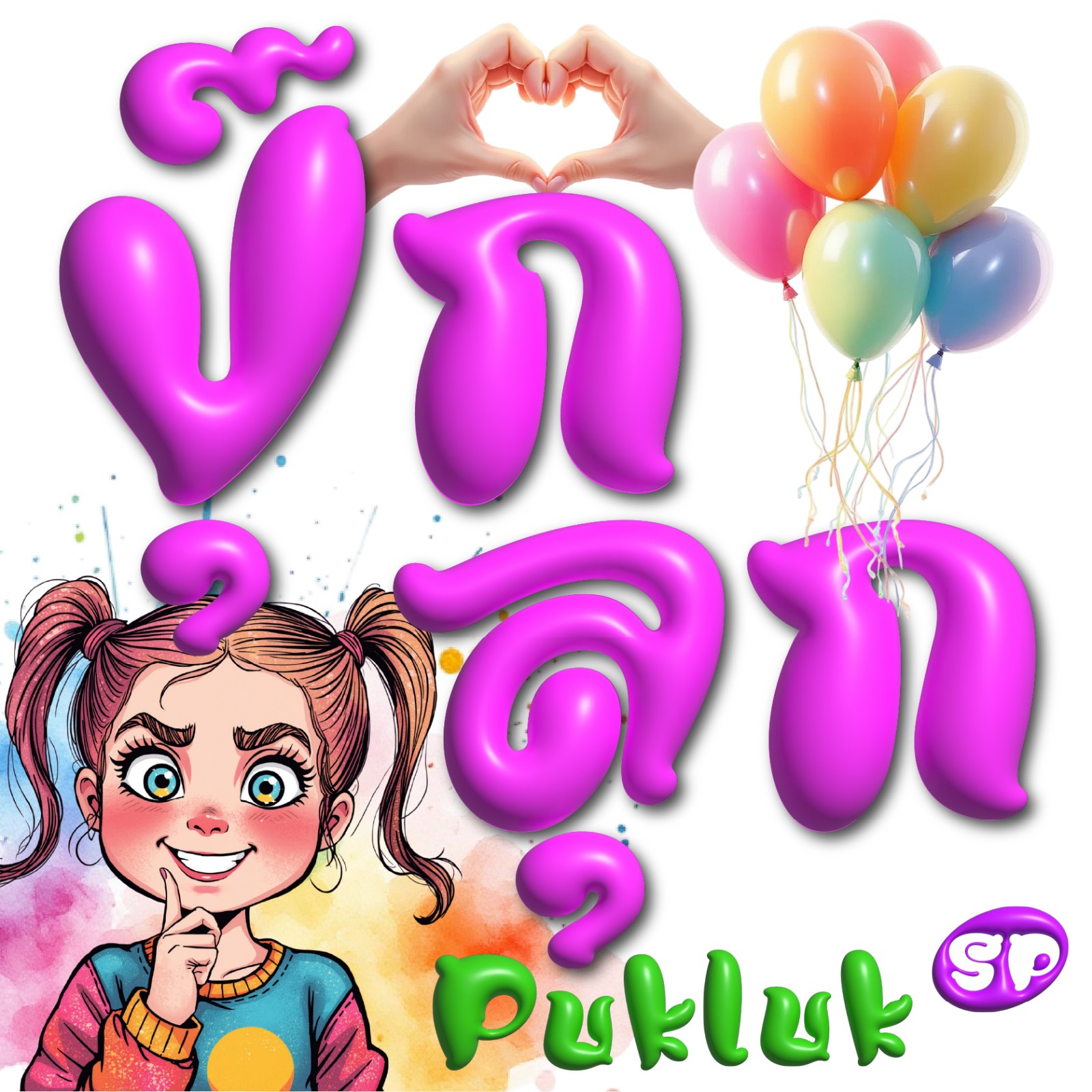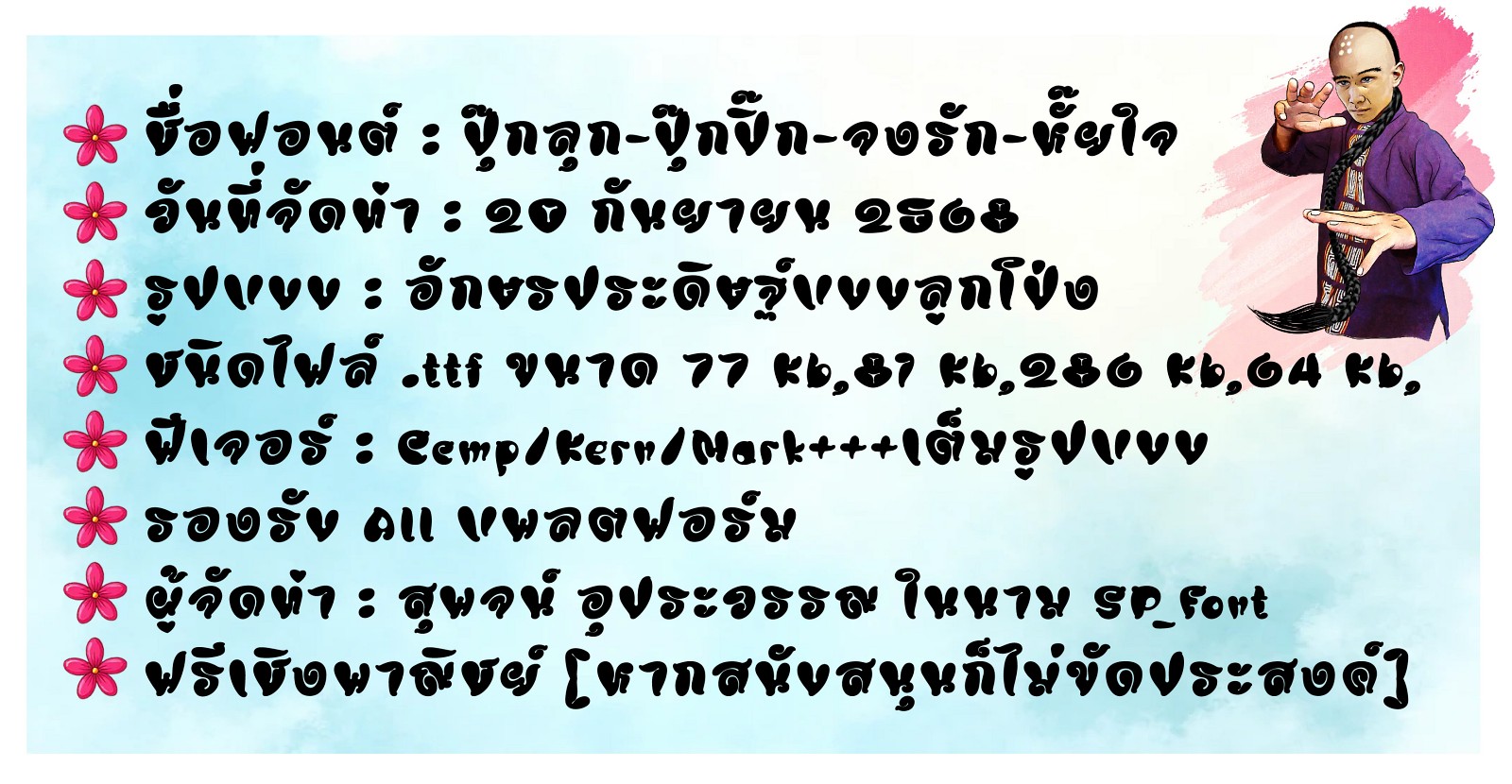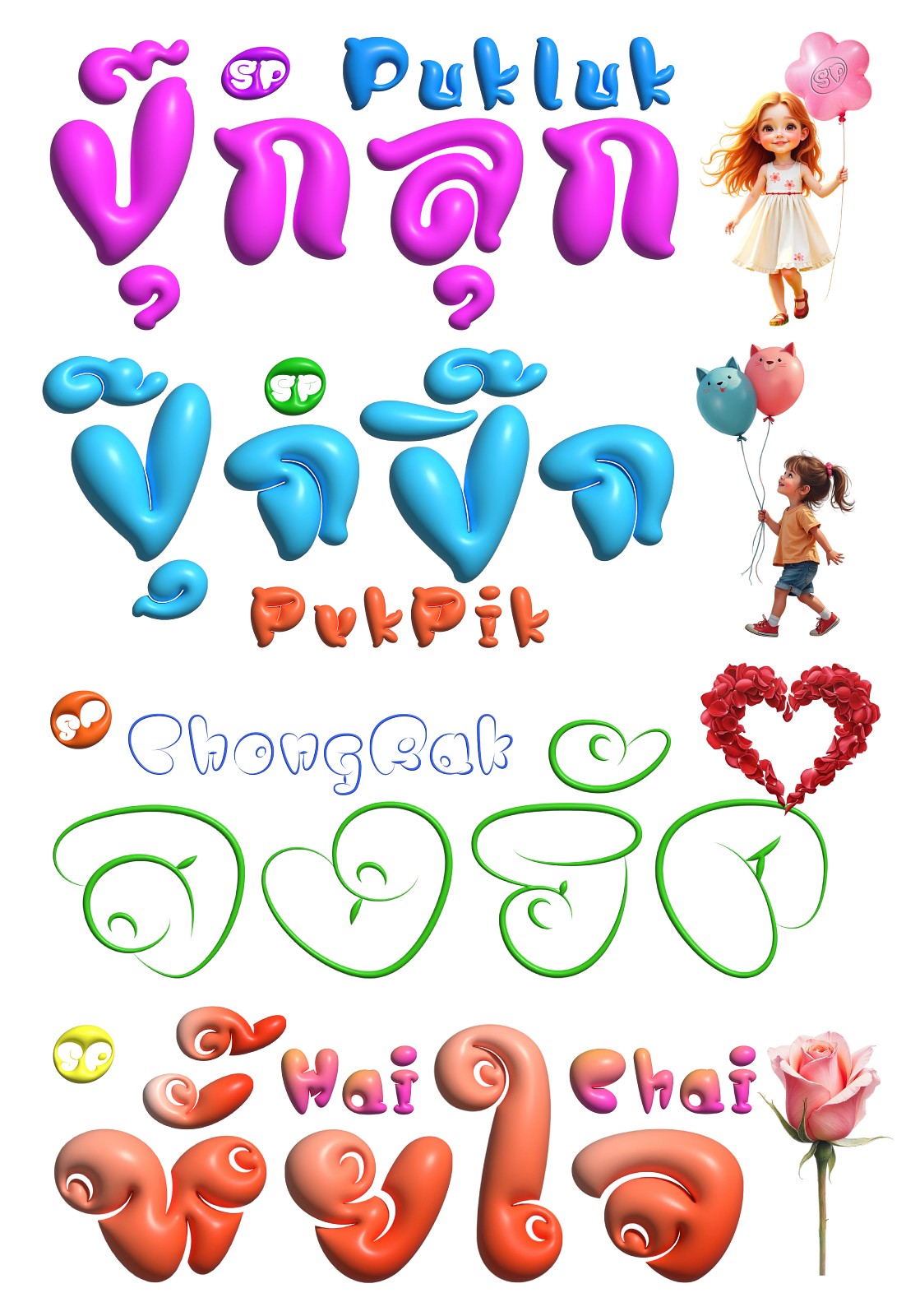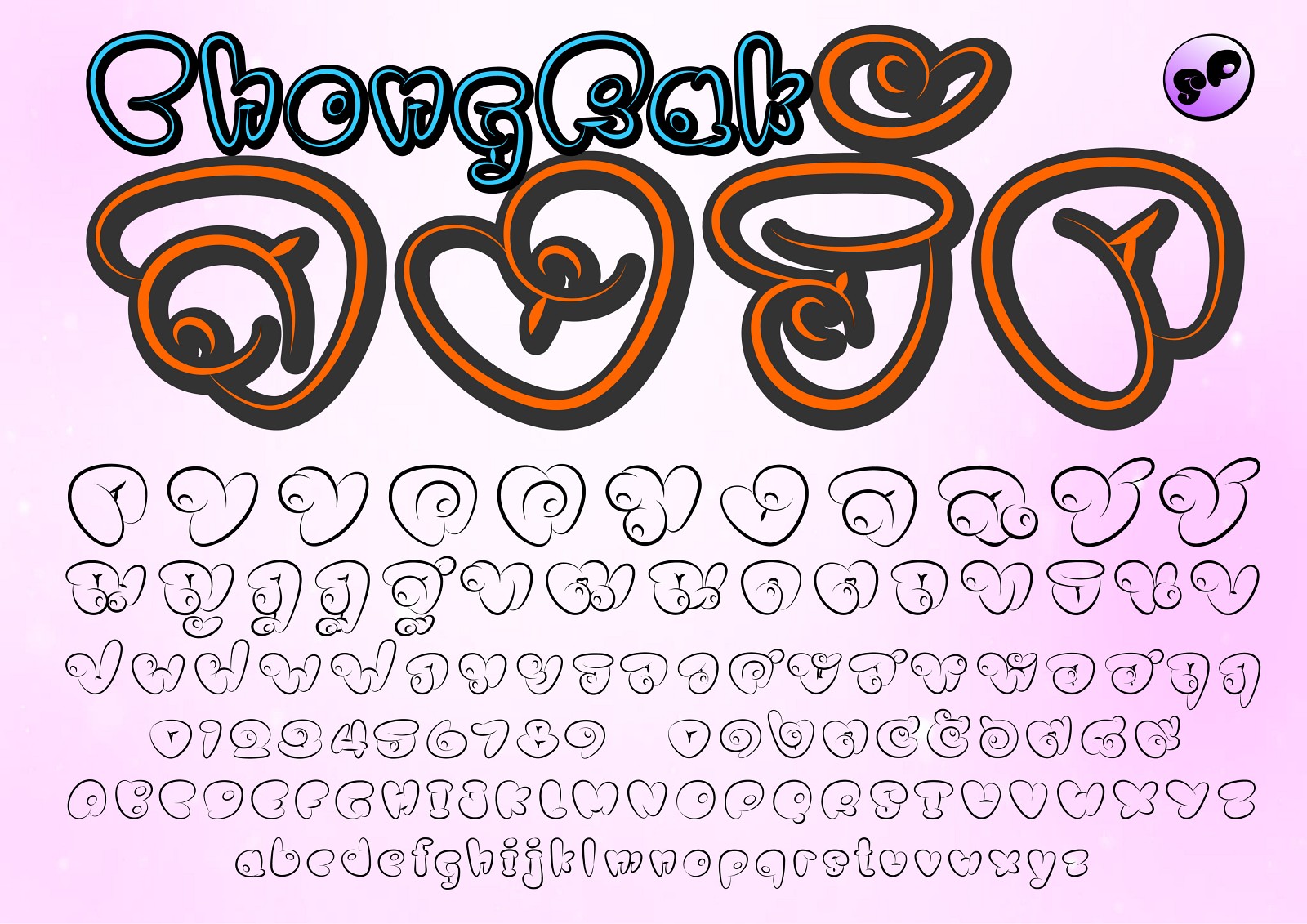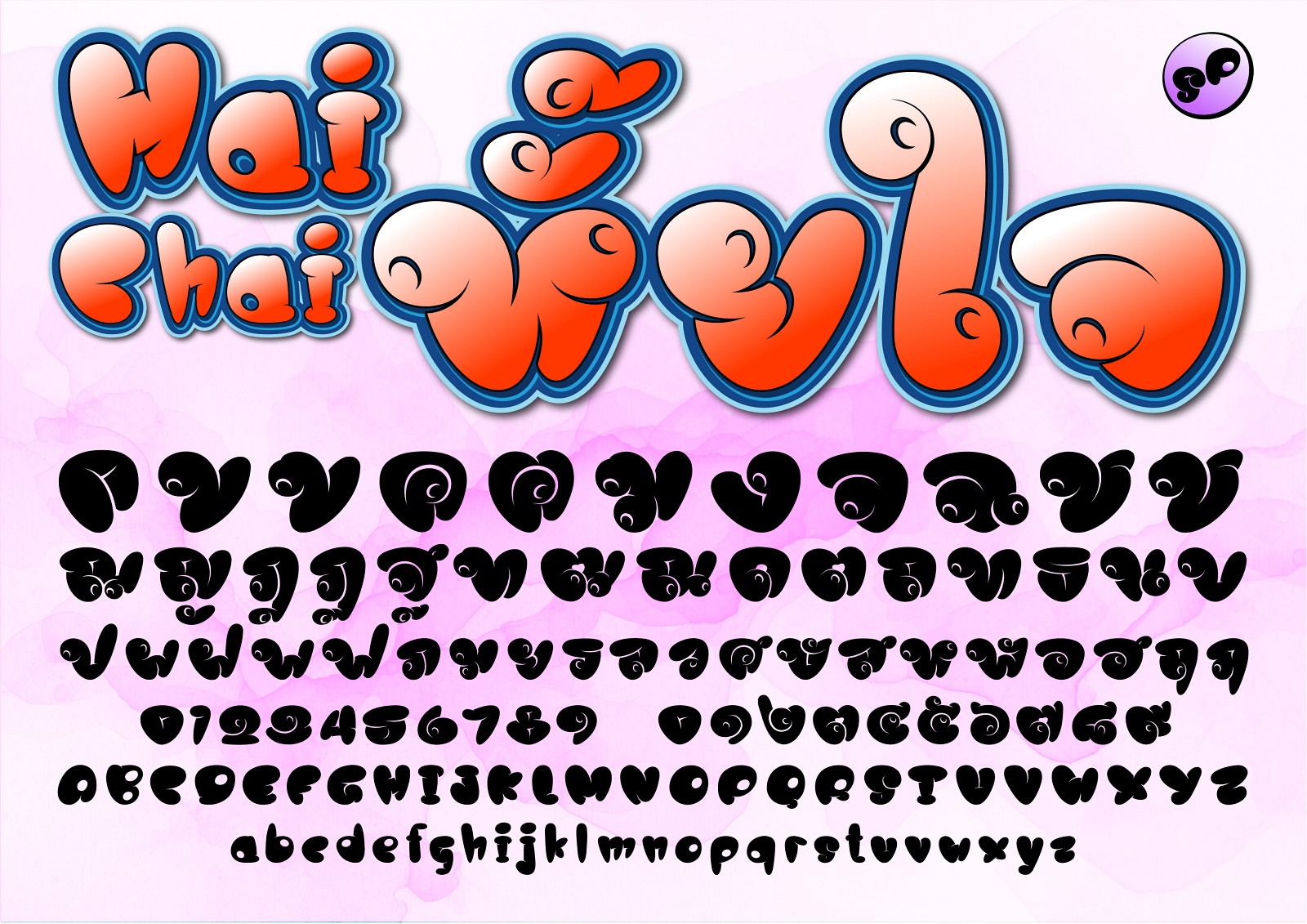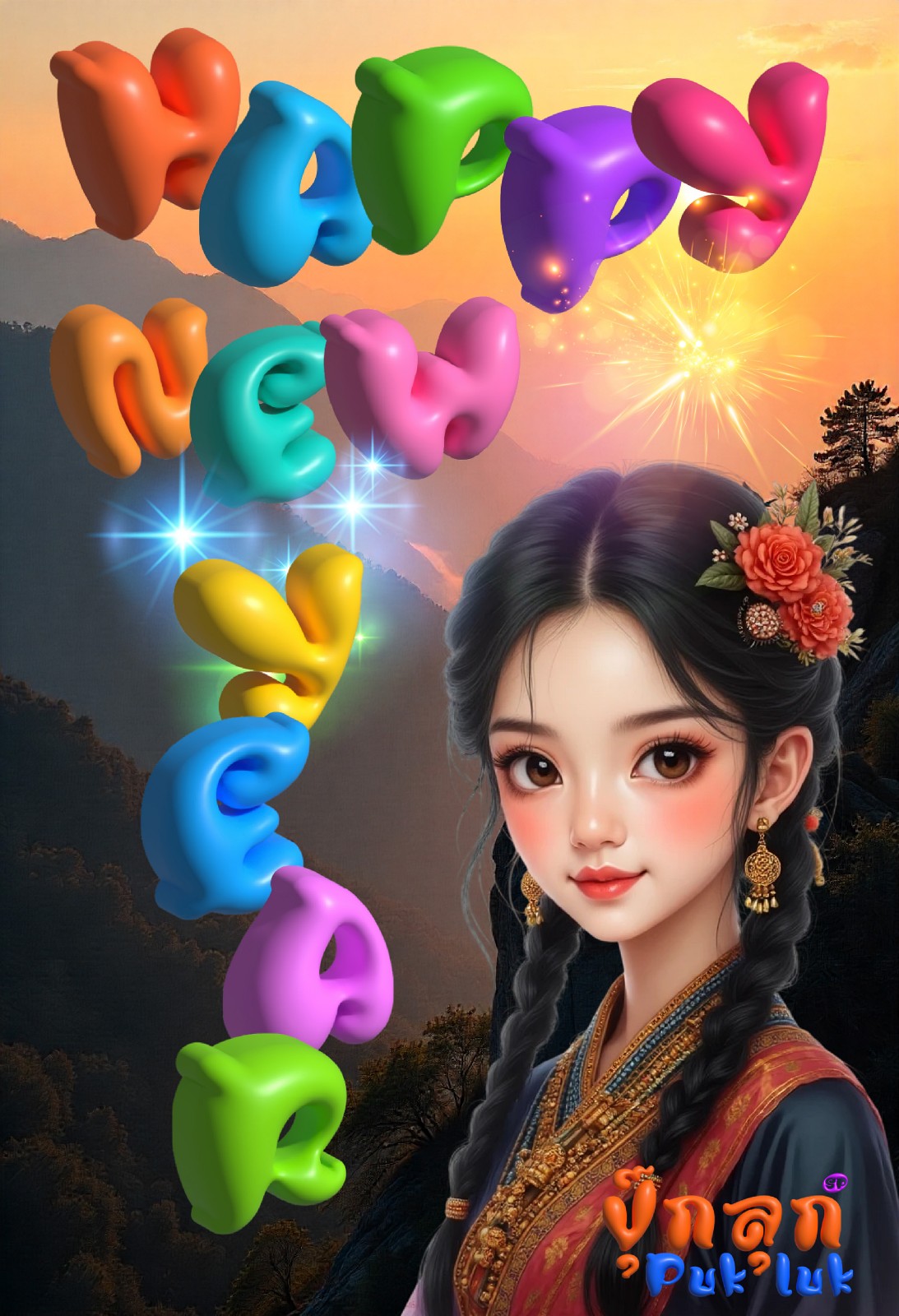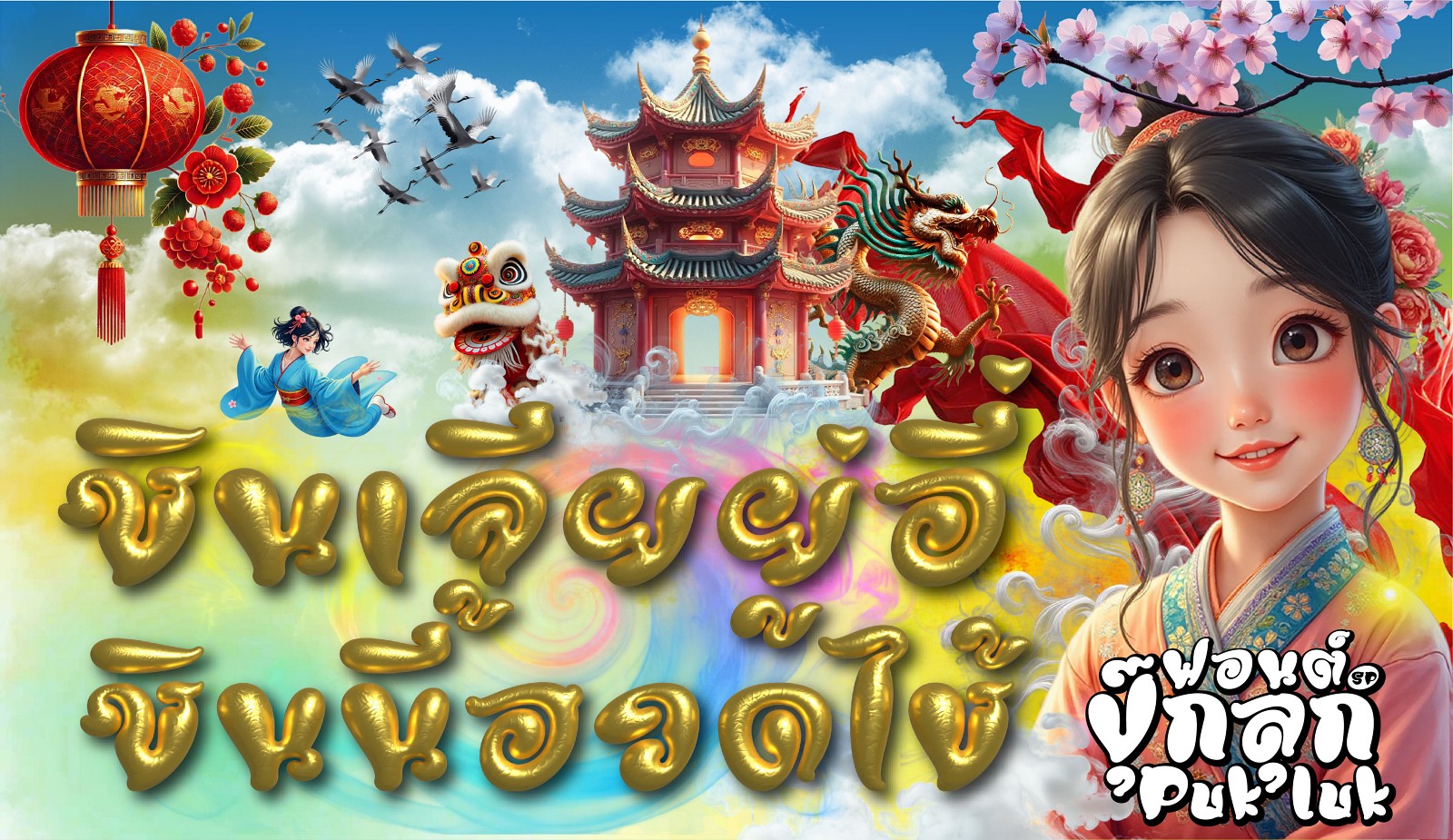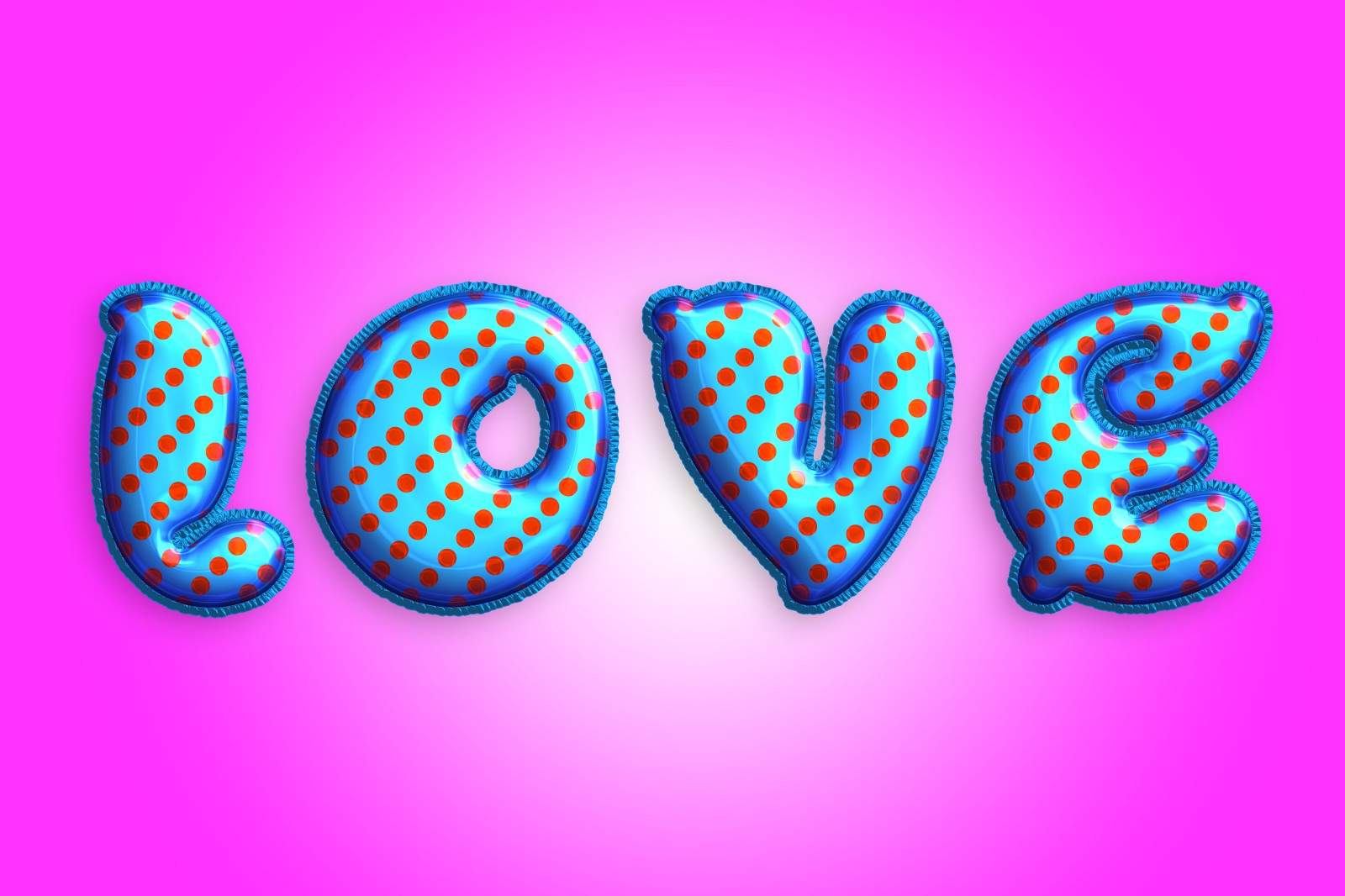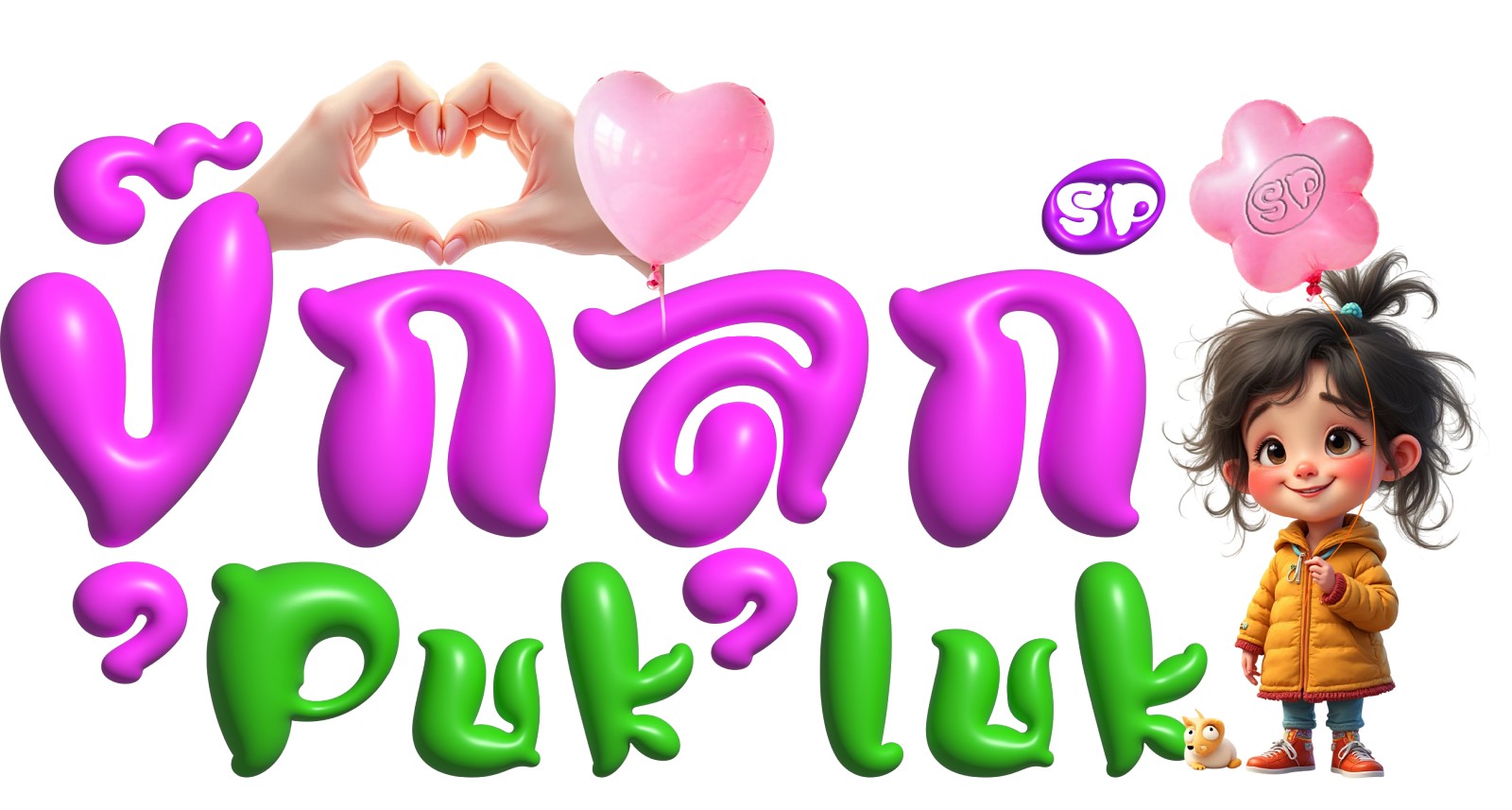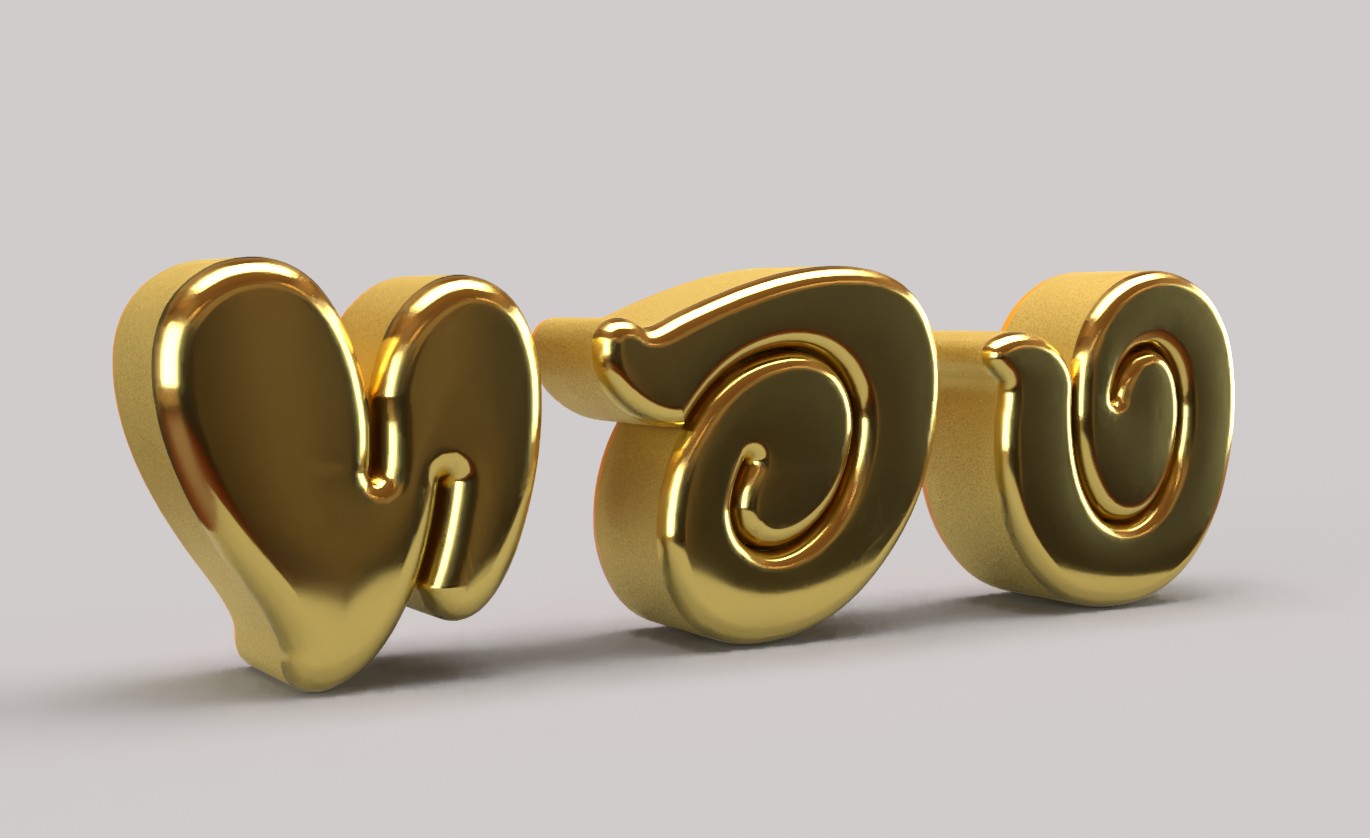
4 ฟอนต์สไตล์ลูกโป่ง ฟอนต์พิเศษเทศกาล ได้แก่ ปุ๊กลุก-ปุ๊กปิ๊ก-จงรัก-หั้ยใจ (SP_PukPik, SP_PukLuk, SP_HaiChai, SP_ChongRak)
4 ฟอนต์ลูกโป่ง (ปุ๊กลุก-ปุ๊กปิ๊ก-จงรัก-หั้ยใจ)